字体设计的方法有很多种,很多小伙伴不知道如何下手,看下面这一波字体的设计能不能给你带来灵感呢。
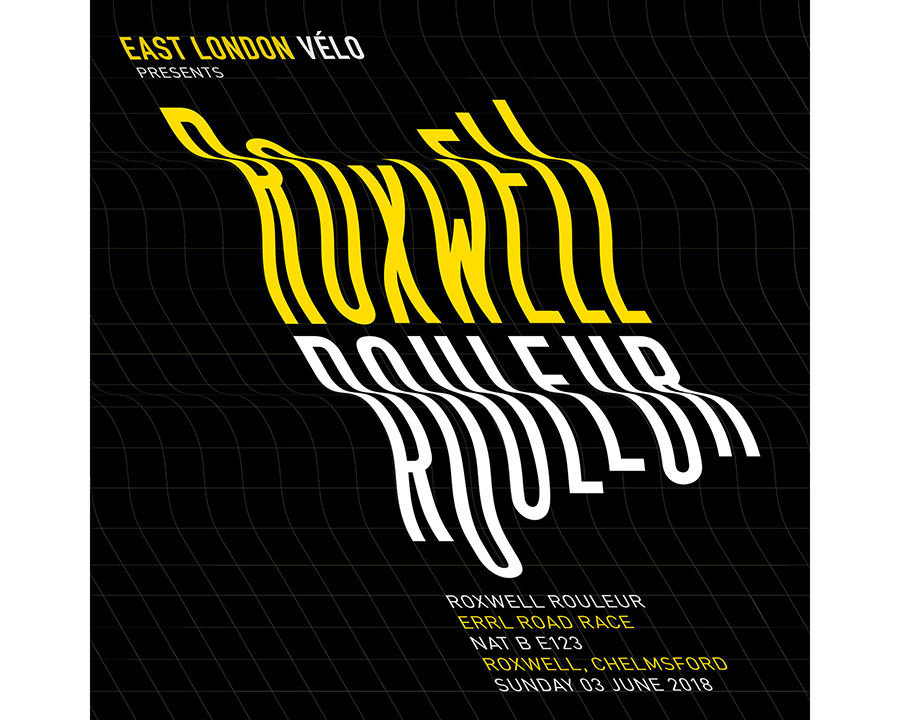
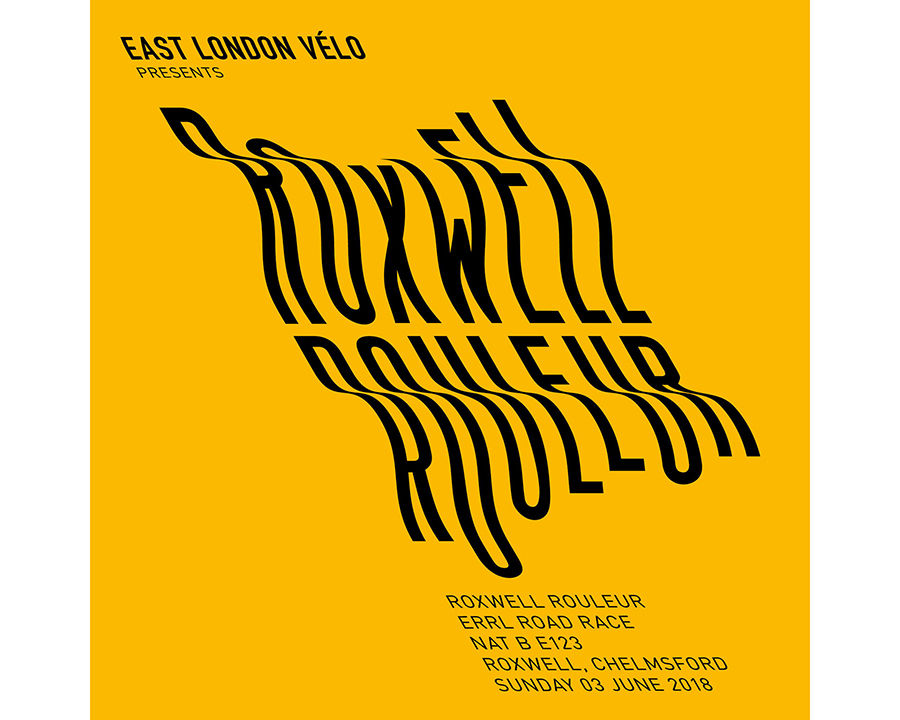
上面这两张波浪形状的字体效果,看起来自然又高级,那是怎么做到的呢,用什么软件实现的呢?
打开AI软件,选择一款无衬线字体,比如Future字体,然后拉长,再进行打散,最后给图形创建封套,选择个别节点进行调节,让字体的形状产生变化,这一步就需要非常有耐心了,字体的好看与否就看这一步的变化了。
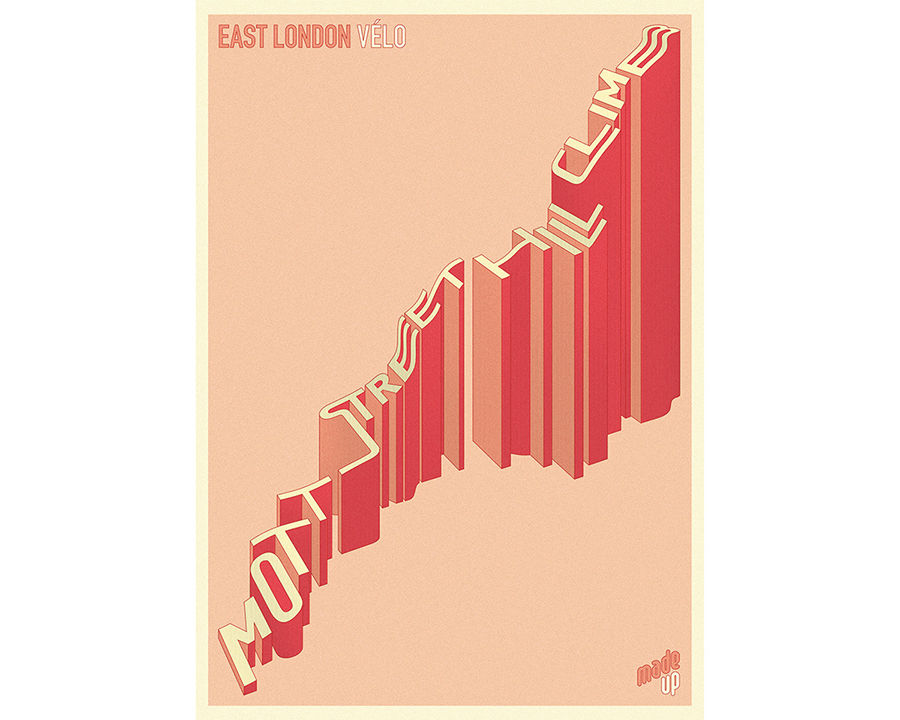
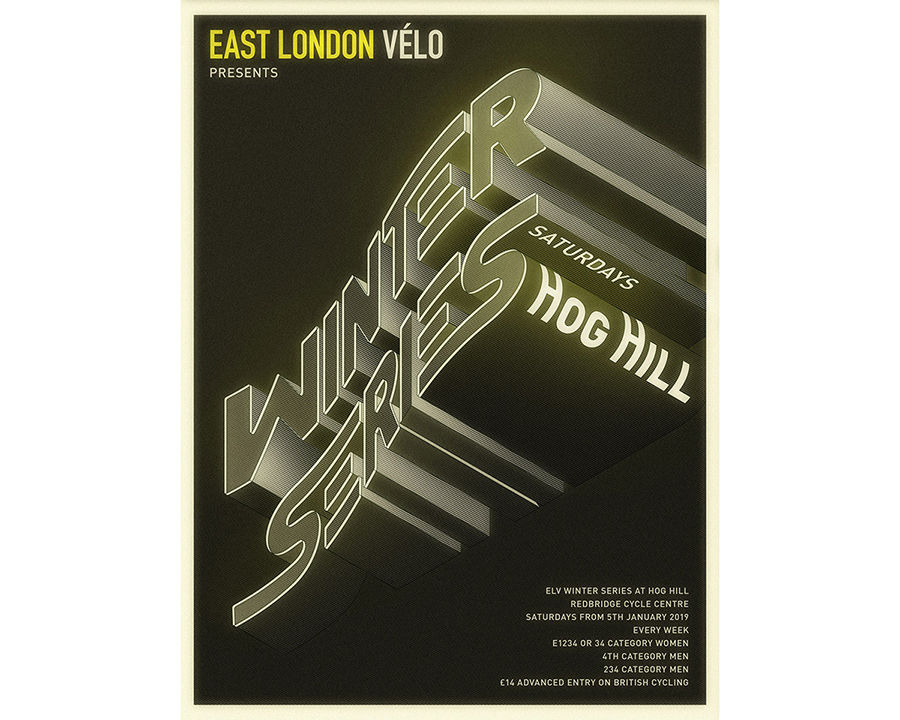
以上四张作品的都是3D立体的字体效果,这个方法比较简单,在AI软件种,选择一款字体,点击【效果】-【3D】-【凸出和斜角】,调整面板里的参数即可实现。
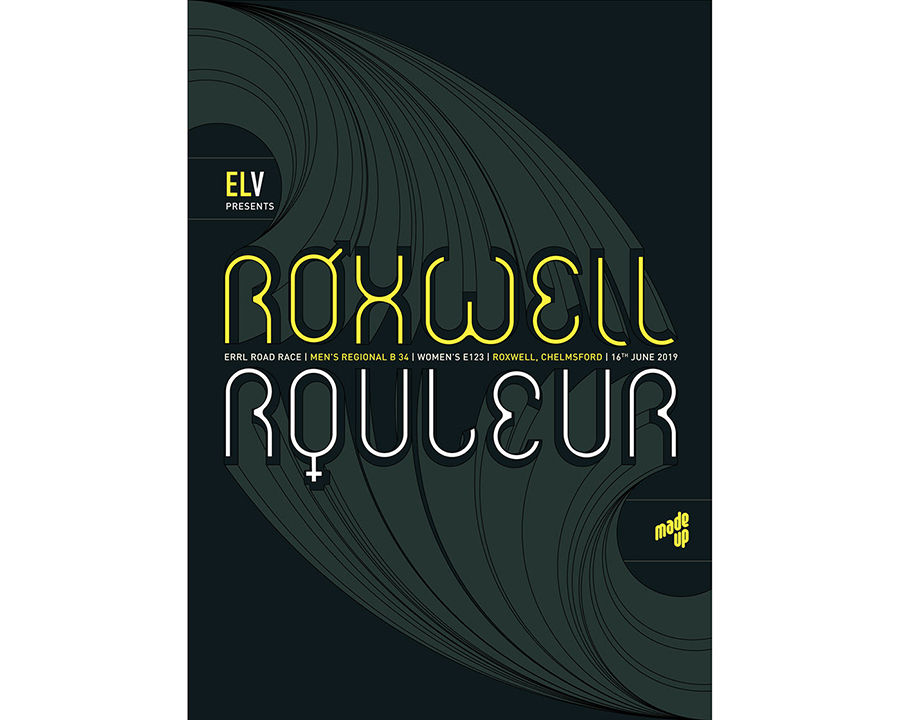
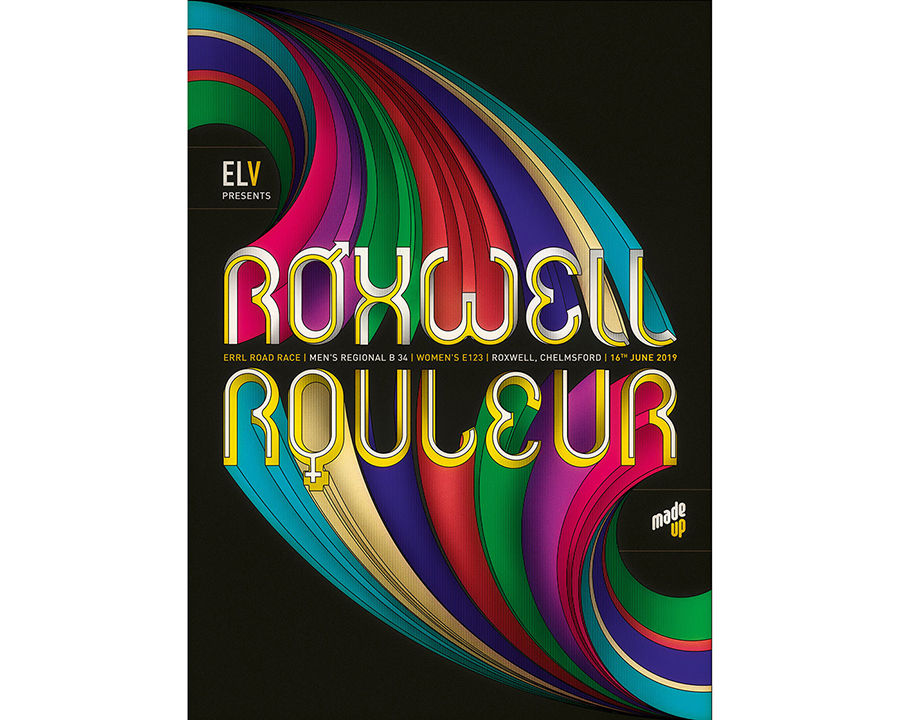
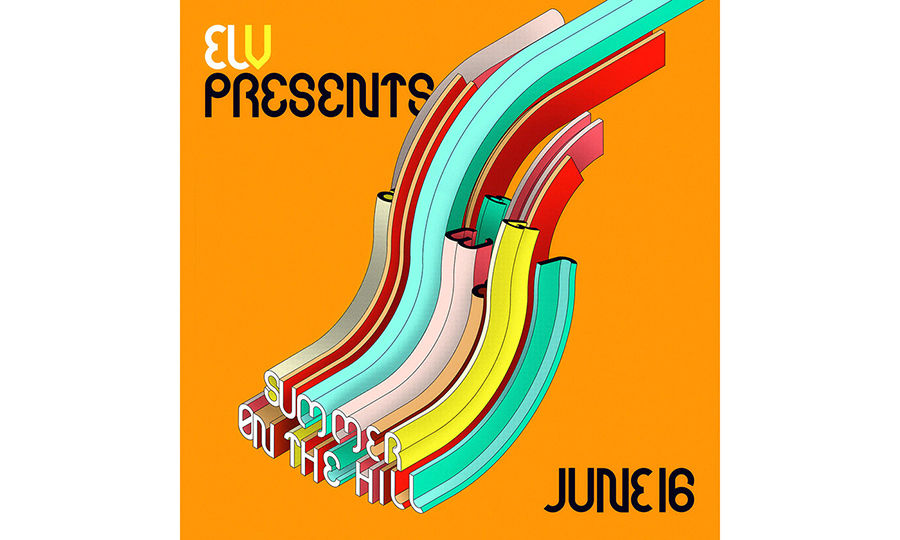
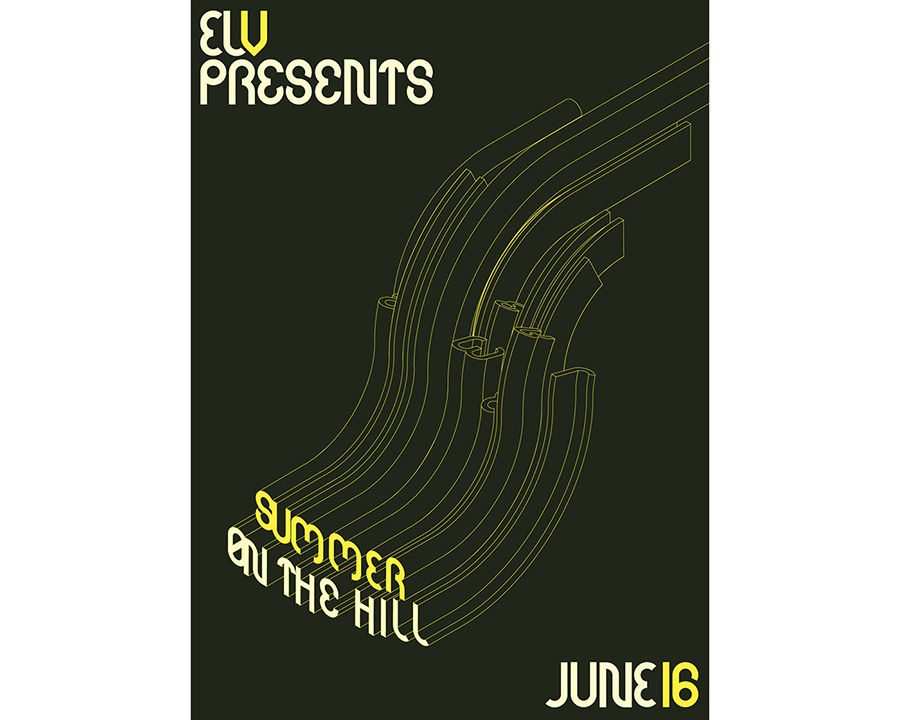
以上四张作品相比上面几张又加大了一层难度,以一个字母为例,选择一个字母并打散,复制一个字母的副本并缩小,然后选择一大一小俩字母,点击【对象】-【混合工具】,在打开的面板种选择【指定的步数】,确定好之后,再选择【对象】-【混合】-【建立】,最后的一步就需要耐心调整颜色了